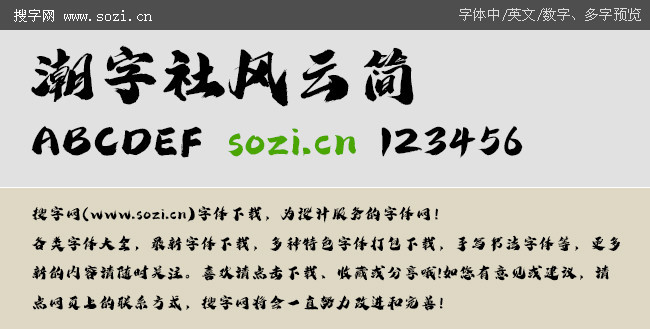
潮字社風(fēng)云簡
搜字網(wǎng)提供一款潮字社風(fēng)云簡中文字體下載,潮字社風(fēng)云體是一款能將書法感和設(shè)計(jì)巧妙地融為一體的繁體樣式,墨漬感十足顯得古方氣息,適用于書籍封面設(shè)計(jì)、報(bào)刊標(biāo)頭設(shè)計(jì),包裝設(shè)計(jì),海報(bào)設(shè)計(jì)等廣告應(yīng)用。(此款為個(gè)人非商用版,如需商用請聯(lián)系銳字工房購買)